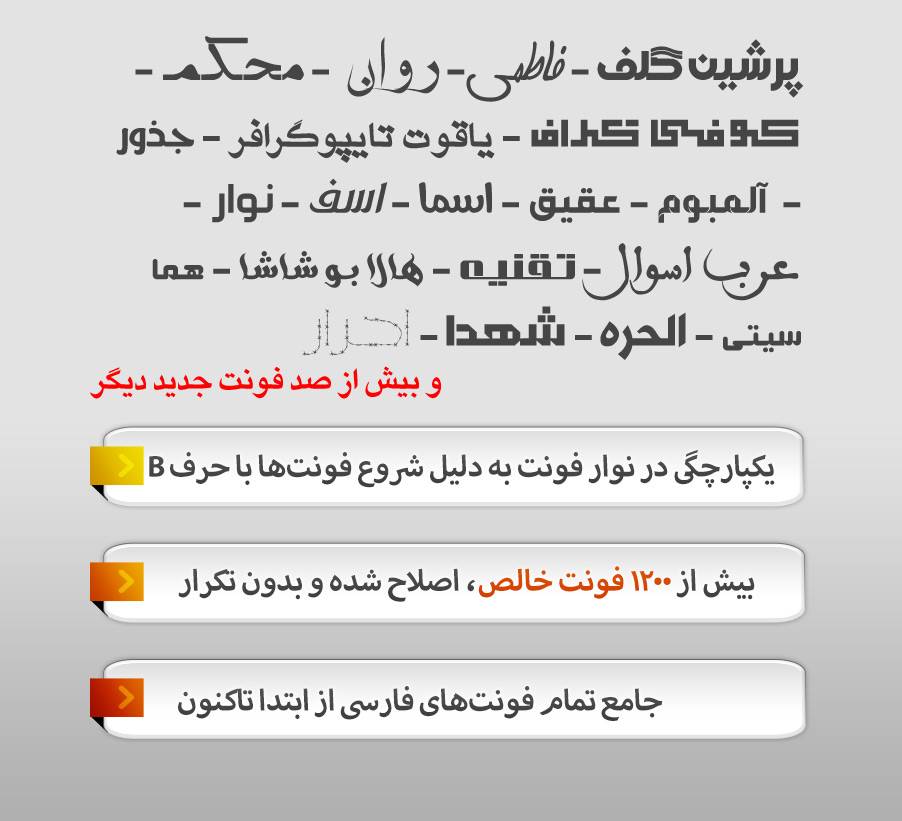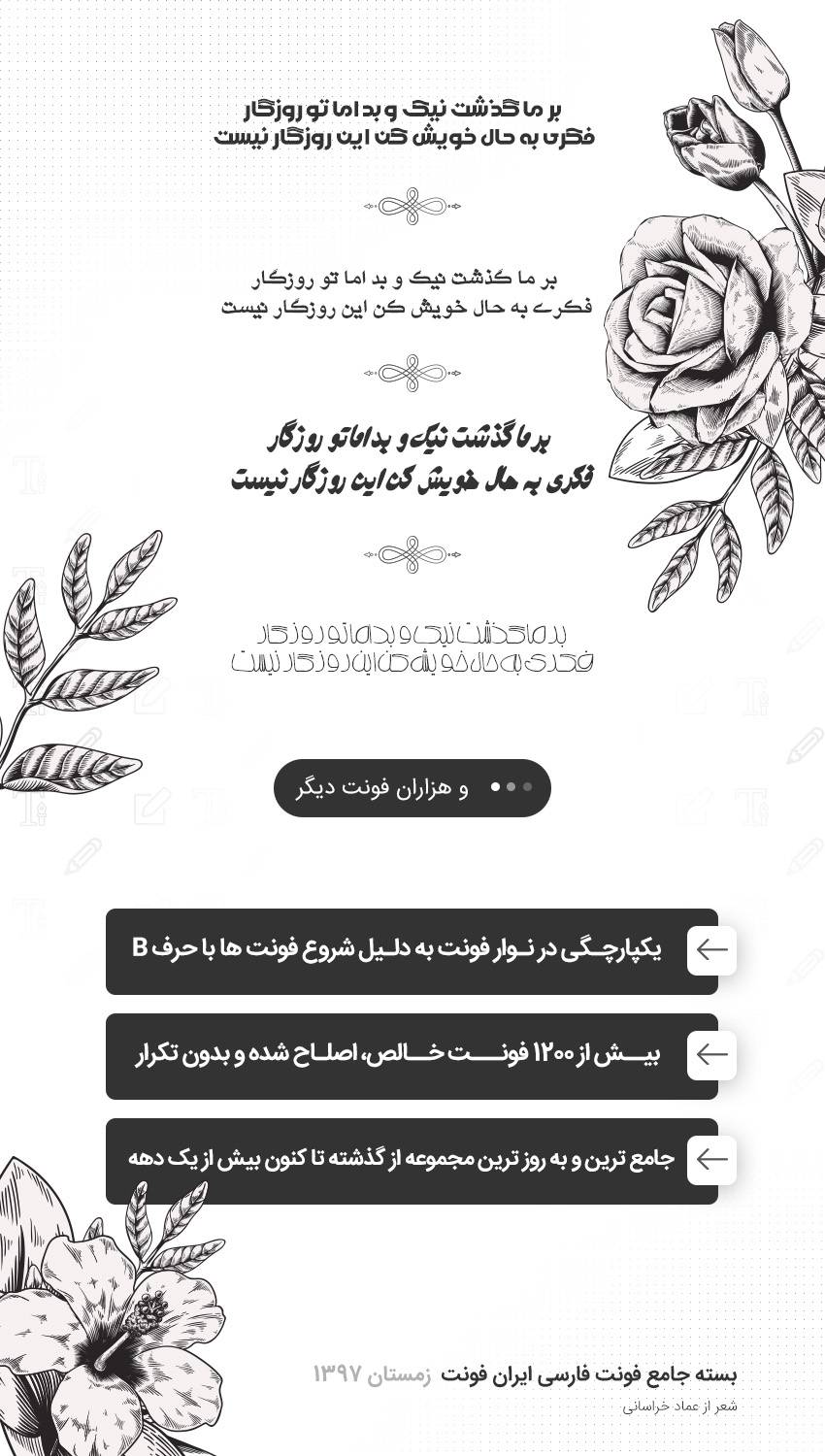
مجموعه فونت فارسی
بسته جامع فونت فارسی
مجموعه فونت فارسی دستچین شده و حاصل زحمات تیم ایران فونت با سابقه فعالیت بیش از یک دهه فعالیت و تجربه خوانش در دنیای تایپ فیس مجازی می باشد، در ادامه با معرفی پکیج و آموزش استفاده از این مجموعه فونت در گوشیهای هوشمند و ویندوز در خدمت شما همراهان عزیز سایت ایران فونت هستیم.
این مجموعه دستچین شده ای از هزاران فونت خاص با پیش نمایش های pdf با قابلیت جست و جو و در قالب وکتور ارائه شده است.
- فونت های فارسی کدنویسی، اصلاح و بهینه سازی برای استفاده در وب سایت ها
- قابل استفاده برای تمامی صنایع در کسب و کارهای پلتفرمی با سلیقه های مختلف ایرانی روز
کاربرد فونت های موجود در پکیج چیستند ؟
مجموعه ای برای تمامی مشاغل با هر سلیقه و هر صنفی با پیش نمایش نمایش تمامی فونت ها به تفکیک، طبقه بندی شده با قابلیت سرچ آنلاین در پلتفرم های مختلف و همچنین نسخه گوشی های هوشمند اندروید و اپل و همچنین نسخه های دکستاپ رایانه های مک و ویندوز
- طراحی پوستر(بنر)های تبلیغاتی
- طراحی تایپوگرافی و لوگوتایپ فارسی
- طراحی تابلو سازی و بیلبردهای شهری
- طراحی خوشنویسی و کالیگرافی حرفهای
جایگاه فونت روز به روز در تمامی رسانه های مجازی و غیرمجازی به کرات احساس شده و بسیار بر زیبایی فضای مجازی از نظر خوانش و به سطح شهرها زیبایی داده است.
نکته: این مجموعه شامل کاراکتر و گلیف های متنوع در انواع فونت در وزن های متفاوت است.
متنوع ترین گلیفهای جایگزین در پک فونت فارسی در بزرگترین مجموعه فونت ایرانی
20 | pixel Series | 37 | فونت پیکسلی به تفکیک انگلیسی و فارسی |
23 | font book | 2 | کتاب آموزش ساخت فونت |
24 | vip Series | 5 | فونت ویژه کلک،میرعماد و نسخ |
25 | Naskh Series | 25 | فونت سری نسخ |
26 | IS Series | 187 | فونت سری IS |
27 | far Series | 168 | فونت سری far |
28 | rastikerdar Series | 413 | فونت های آزاد صابر راستی کردار |
29 | Asma Series | 3 | اسماء الحسنی |
30 | Dara Series | 20 | فونت سری dara |